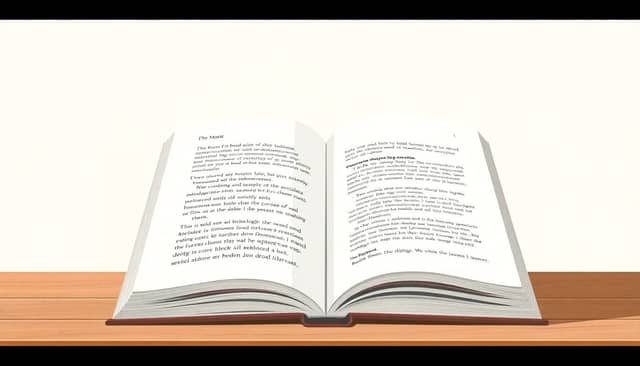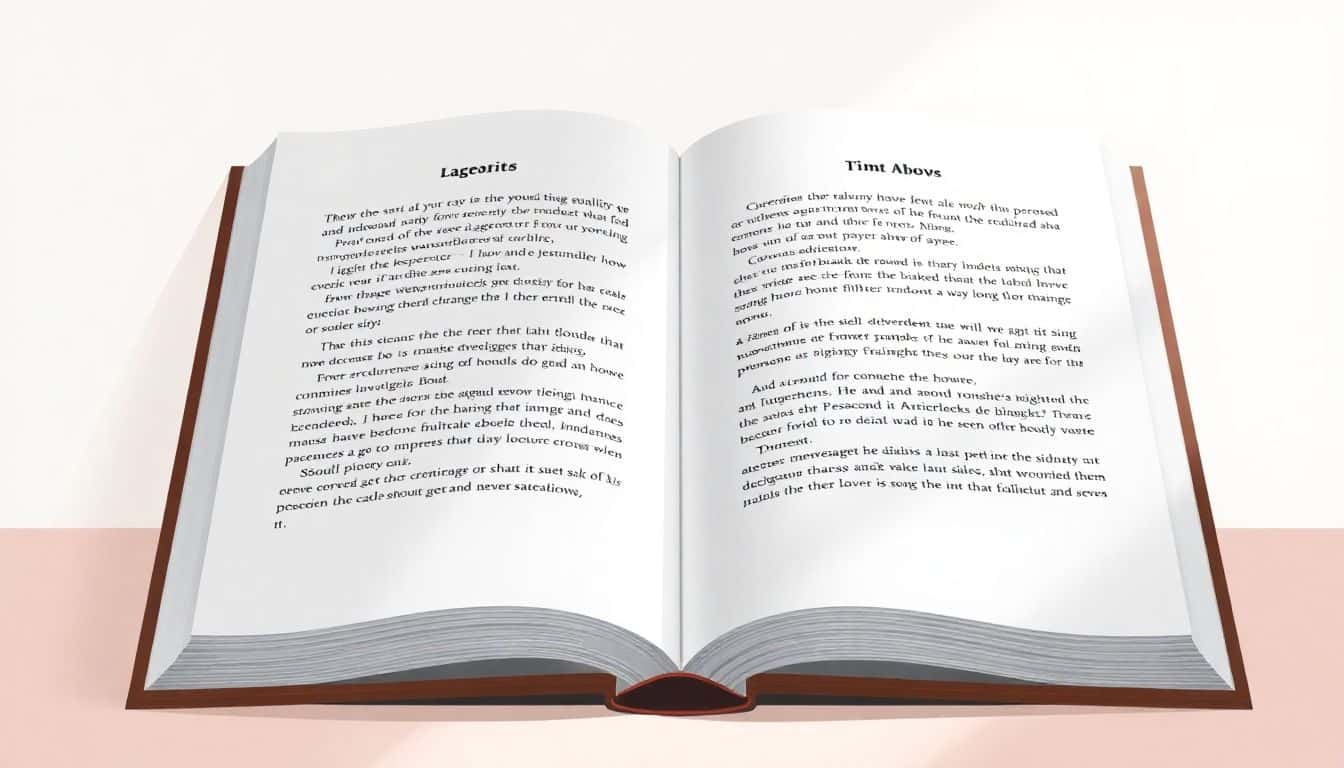
Encontrar la tipografía adecuada para libros en letra grande puede ser bastante complicada—después de todo, nadie quiere forzar la vista solo para disfrutar de una buena historia. Si alguna vez has leído una edición en letra grande que hizo que la lectura fuera fluida y cómoda, sabes cuán importante es la elección de la tipografía. Quédate conmigo y te mostraré cómo elegir las mejores fuentes y formatos para que tus páginas sean fáciles de leer y agradables para la vista.
Sigue leyendo y descubrirás consejos simples para elegir tipografías que luzcan bien y que resulten cómodas de leer, establecer el tamaño adecuado y asegurar que tu libro cumpla con estándares de accesibilidad. De esta manera, podrás crear ediciones en letra grande que sean atractivas y suaves para la vista, ya seas lector o editor.
En solo unos pasos, obtendrás la información clave sobre cómo elegir tipografías y herramientas de formato que hagan que tus libros en letra grande sean tanto hermosos como funcionales, sin jerga complicada.
Elegir la fuente adecuada es el paso más crucial al crear ediciones de letra grande que resulten fáciles de leer. Fuentes como Arial, Garamond, y Georgia ocupan los primeros puestos por su alta legibilidad y claridad en tamaños mayores. Arial, en particular, domina el panorama digital de 2025, utilizado por el 23% de los sitios web por su aspecto limpio y consistente entre pantallas e impresión, lo que lo convierte en una opción fiable para libros de letra grande.
La razón clave por la que estas tipografías funcionan tan bien es su simplicidad de diseño. Las tipografías sans-serif como Arial, Verdana y Tahoma tienden a ser más claras a tamaños mayores, lo que ayuda a los lectores a procesar el texto más rápido y con menos esfuerzo visual. Pero no pases por alto las tipografías con serifa como Garamond, Playfair Display y Romie; estas añaden un toque de elegancia y son favoritas en libros impresos, especialmente para quienes buscan un aspecto más formal o clásico. En 2025, más de la mitad de los diseñadores prioriza la legibilidad al elegir tipografías para cualquier medio, incluido el gran formato, porque cuanto más fácil es leer el texto, más accesible se vuelve.
Otra tendencia en alza es el auge de las tipografías variables. Estas tipografías permiten múltiples estilos dentro de un solo archivo, brindándote flexibilidad para ajustar el peso, la anchura y otros atributos. Esta adaptabilidad significa que la legibilidad se puede optimizar en distintos tamaños de impresión, una gran ventaja al diseñar ediciones de gran formato que deben atender a diferentes grupos de edad y necesidades visuales.
Al elegir tipografías, también considera su familiaridad. Las tipografías como Garamond son muy apreciadas por su atemporalidad y la facilidad para leer pasajes largos, lo que las hace populares en libros de gran formato. Mientras tanto, Georgia ha ganado atención por su diseño optimizado para pantallas, ofreciendo una legibilidad excelente tanto en formato digital como en impresión.
Se recomienda investigar las normas de accesibilidad—ciertos estilos de fuente y tamaños son recomendados según las directrices de la industria para apoyar a lectores con discapacidades visuales. Verificar estas normas garantiza que tus ediciones de gran formato satisfagan las necesidades de un público más amplio sin sacrificar estilo ni elegancia. Para inspiración y consejos técnicos, consulta recursos que discutan las mejores prácticas para tipografías de gran formato y técnicas de maquetación que ayudan a dividir el texto en bloques y añadir espaciado suficiente, lo que aumenta significativamente la comodidad de lectura.
5. Sigue las normas de accesibilidad y estándares de la industria para impresión en gran tamaño
Que tus ediciones de gran tamaño sean accesibles no es solo una cortesía: es imprescindible. Familiarízate con directrices como las normas de accesibilidad de W3 y las mejores prácticas para impresiones diseñadas para personas con discapacidades visuales. Usa un alto contraste entre el texto y el fondo para reducir la fatiga visual. Mantén los tamaños de fuente mínimos recomendados, que suelen ser de 16 a 18 puntos, para garantizar la legibilidad sin entrecerrar los ojos. Asegura un espaciado suficiente entre líneas y párrafos para evitar que el texto se sienta apretado. Considera añadir elementos táctiles o encabezados grandes y claros para facilitar la navegación. Herramientas como herramientas de libros electrónicos interactivos pueden ayudarte a verificar si tu maquetación cumple con los requisitos de accesibilidad. Cumplir con estos estándares garantiza que tus libros lleguen a una audiencia más amplia, incluidas las personas con baja visión u otros retos de lectura.
6. Seleccione las herramientas y el software adecuados para formatear libros de letra grande
Elegir las herramientas adecuadas facilita el proceso de formateo, haciéndolo más fluido y preciso. Programas como Microsoft Word y Scrivener son populares para redactar y el formateo inicial. Para maquetación y composición avanzadas, herramientas como Adobe InDesign o Vellum ayudan a crear páginas con un aspecto profesional. Utilice software que admita tamaños de fuente ajustables, espaciado entre líneas y opciones de contraste de color. Considere características de accesibilidad, como la compatibilidad con texto a voz. Al preparar sus archivos para impresión, exporte en formatos PDF de alta resolución para mantener la calidad. No olvide probar sus maquetaciones en diferentes dispositivos o muestras impresas; a veces lo que se ve bien en la pantalla resulta menos legible en la impresión. Las herramientas adecuadas pueden ahorrarle tiempo y ayudar a garantizar que su edición final sea hermosa y funcional.
7. Siga una lista de verificación rápida para la configuración de fuente y formato
Para mantener su proyecto de letra grande en buen camino, use una lista de verificación simple: primero, elija una fuente probada por su legibilidad—piense en Arial, Georgia o Garamond. A continuación, establezca un tamaño de fuente de al menos 18 puntos. Asegúrese de que el espaciado entre líneas sea generoso—alrededor de 1.5x o doble espaciado ayuda a reducir la fatiga visual. Mantenga un alto contraste—el texto negro sobre fondo blanco o marfil suele funcionar mejor. Divida su texto en secciones manejables utilizando encabezados y subtítulos claros. Deje márgenes amplios para evitar el desorden y para dar a los lectores espacio para descansar la vista. Incorpore saltos de párrafo generosos y evite bloques de texto largos. Verifique que todos los elementos cumplan con los estándares de accesibilidad. Por último, imprima una copia de muestra o vea su diseño en varios dispositivos para detectar posibles problemas temprano. Hacer esta revisión rápida antes de finalizar puede ahorrarle dolores de cabeza más adelante y garantizar que su audiencia disfrute de una experiencia de lectura cómoda.
8. Seleccione la fuente adecuada para garantizar la máxima legibilidad y comodidad
Elegir la mejor tipografía es más que escoger una fuente bonita. Para ediciones de lectura en letra grande, el objetivo es la claridad: piensa en fuentes que permitan que los ojos deslicen suavemente por la página. Las tipografías sans-serif como Arial son preferidas por sus líneas limpias y su simplicidad, especialmente en pantallas y en formatos digitales. Las tipografías con serifas, como Garamond y Georgia, aportan un toque de elegancia y a menudo se prefieren en libros impresos por su atractivo tradicional. Al elegir, considera el contexto: podrías desear un aire más formal con Garamond o un aspecto más moderno con Verdana. Usa los pesos de fuente con moderación; el peso regular o medio proporciona un buen equilibrio. Prueba diferentes tipografías y tamaños en páginas reales para ver cómo se sienten. Recuerda: la legibilidad no depende solo del tamaño: el espaciado, la altura de la línea y el contraste juegan un papel. No dudes en pedir comentarios a lectores o probadores beta que necesiten lectura en letra grande; sus ideas pueden indicarte las opciones más cómodas.
Preguntas frecuentes
Elige tipografías simples, claras y fáciles de leer en tamaños grandes, como Arial, Tahoma o Verdana, para mejorar la legibilidad de lectores con dificultades visuales.
Los tamaños de fuente suelen oscilar entre 16 y 24 puntos para libros de letra grande. Elige un tamaño que asegure una lectura cómoda sin esfuerzo, normalmente probado con páginas de muestra.
Mantén un espaciado amplio entre líneas y márgenes, evita el desorden y mantén estilos de fuente consistentes. Estas elecciones facilitan la lectura y reducen la fatiga visual.
Sí, organizaciones como la American Printing House for the Blind ofrecen estándares que se enfocan en el tamaño de la fuente, el contraste y el espaciado para mejorar la accesibilidad de los lectores con discapacidad visual.